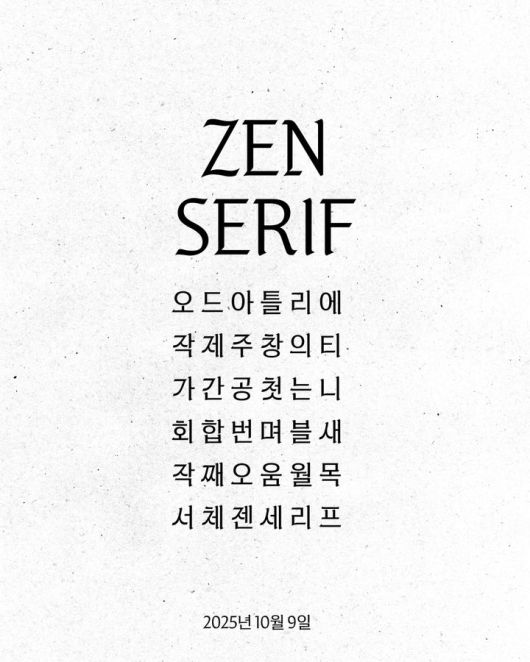
[서울=뉴시스]이재훈 기자 = K팝 간판 걸그룹 '블랙핑크' 멤버 겸 솔로 가수 제니(JENNIE)가 새로운 한글 폰트로 한국의 아름다움을 알린다.
제니 소속사 OA엔터테인먼트(ODDATELIER)는 한글날인 9일 공식 홈페이지와 소셜 미디어 채널을 통해 신규 폰트 '젠 세리프(ZEN SERIF)' 출시 소식을 알렸다.
더 많은 사람들이 한글을 편리하고 아름답게 사용할 수 있길 바라는 마음으로 전통의 미감과 현대적 감각을 담아냈다는 설명이다.
OA엔터는 또한 메타(Meta)와 협업을 통해 인스타그램 숏폼 영상 편집 앱 '에디트(Edits)'에 한글 폰트를 최초로 등록, 이날부터 전세계 모든 앱 사용자가 해당 신규 폰트를 무료로 자유롭게 사용할 수 있다.
'젠 세리프'는 장식을 최소화해 본질을 살리고, 딱딱한 인상을 덜어내면서 유연한 곡선을 더해 OA엔터의 섬세함을 담았다. 서양의 전통 서체인 블랙레터와 한글을 결합해 드문 조합을 완성했다.
OA엔터는 "'젠 세리프' 폰트는 제니와 OA엔터의 정체성을 담아 전 세계에 한글의 아름다움을 알리기 위해 출시된 것으로, 한글날을 맞이해 폰트가 출시돼 더욱 의미가 뜻깊다"고 특기했다.
앞서 제니는 첫 번째 정규 앨범의 수록곡 '젠(ZEN)'과 '서울 시티(Seoul City)'로 한국의 멋을 세계에 알렸다. 서울관광 명예홍보대사로 활동하는 등 다양한 활동을 통해 한국에 대한 특별한 사랑과 자부심을 드러냈다.